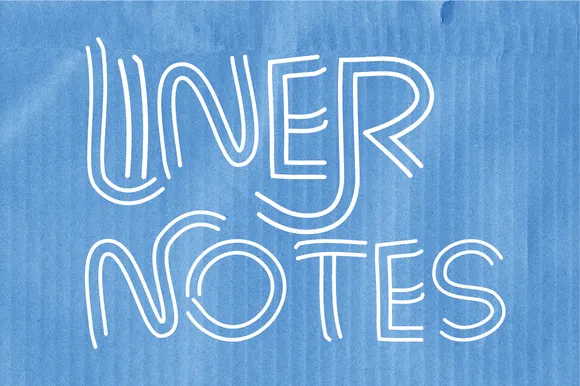
A Liner Notes é uma fonte exuberante e desenhada para fins visuais memoráveis. Ela é divertida e desenhoada com traços ásperos, especialmente adequada para uso no estilo de notas de pista de um público jovem ou versátil, que pode se adaptar tanto aos posters quanto às letras grandes na mídia. Esse fonte, criado pelo designer Hamilton, tem muitas características únicas e atraentes. Além do conjunto completo de 260 caracteres, há várias variações no alfabeto padrão, incluindo as inúmeras particularidades estrangeiras que fazem o uso da Liner Notes algo realmente distinto. Com mais que isso, também oferece letras com ligações extras e detalhes finos para quem usa a fonte em ambientes digitais como o OpenType ou via painéis de caracteres no Glyphs. Com os novos elementos incorporados em formações web e sinônimos da linguagem digital, a Liner Notes pode ser usada não apenas para fazer letras grandiosas e posters memoráveis, mas também para expressar a onda das plataformas digitais modernas. Ela é uma fonte perfeita tanto para designers gráficos quanto para qualquer artista que deseja dar um toque especial em seu trabalho.